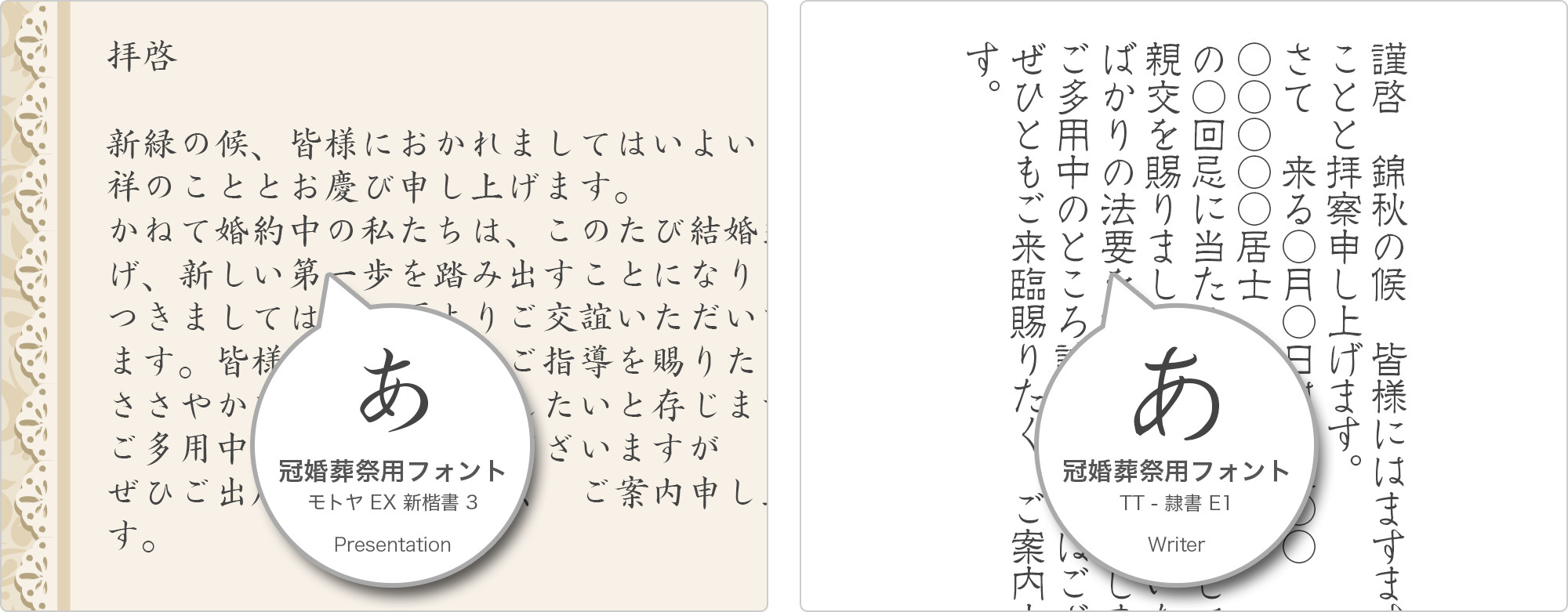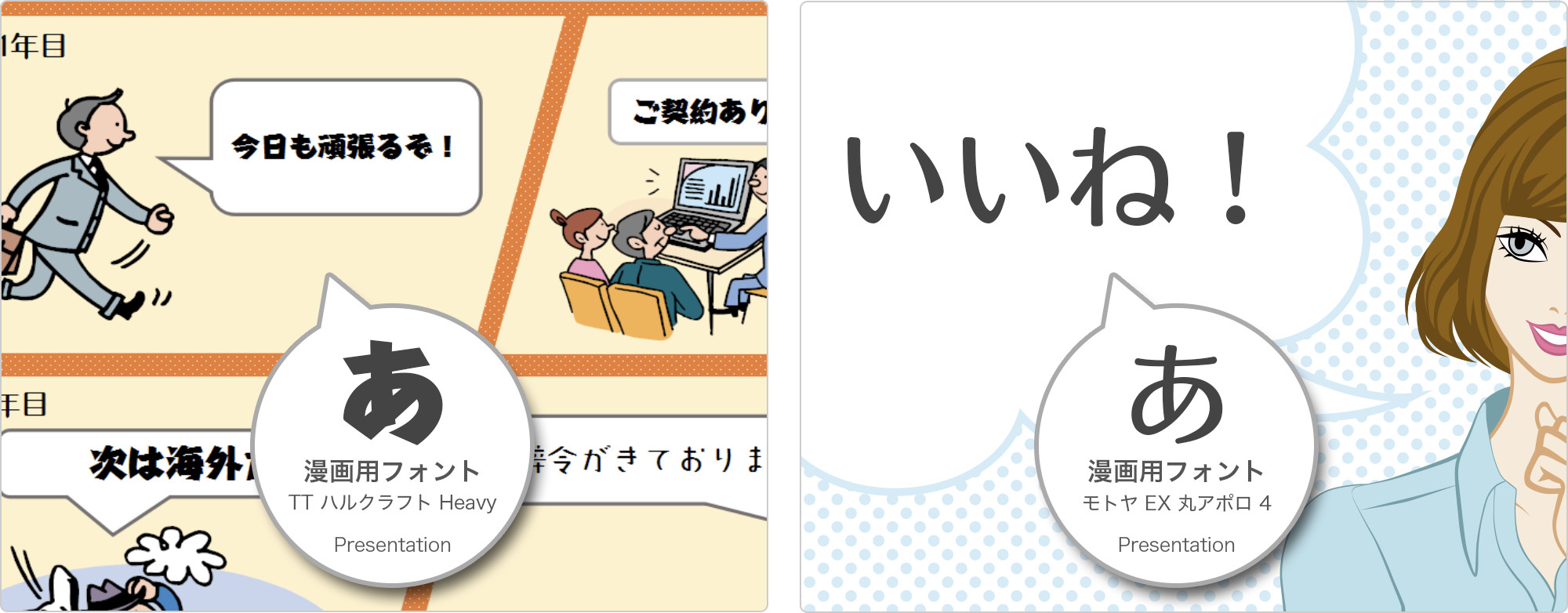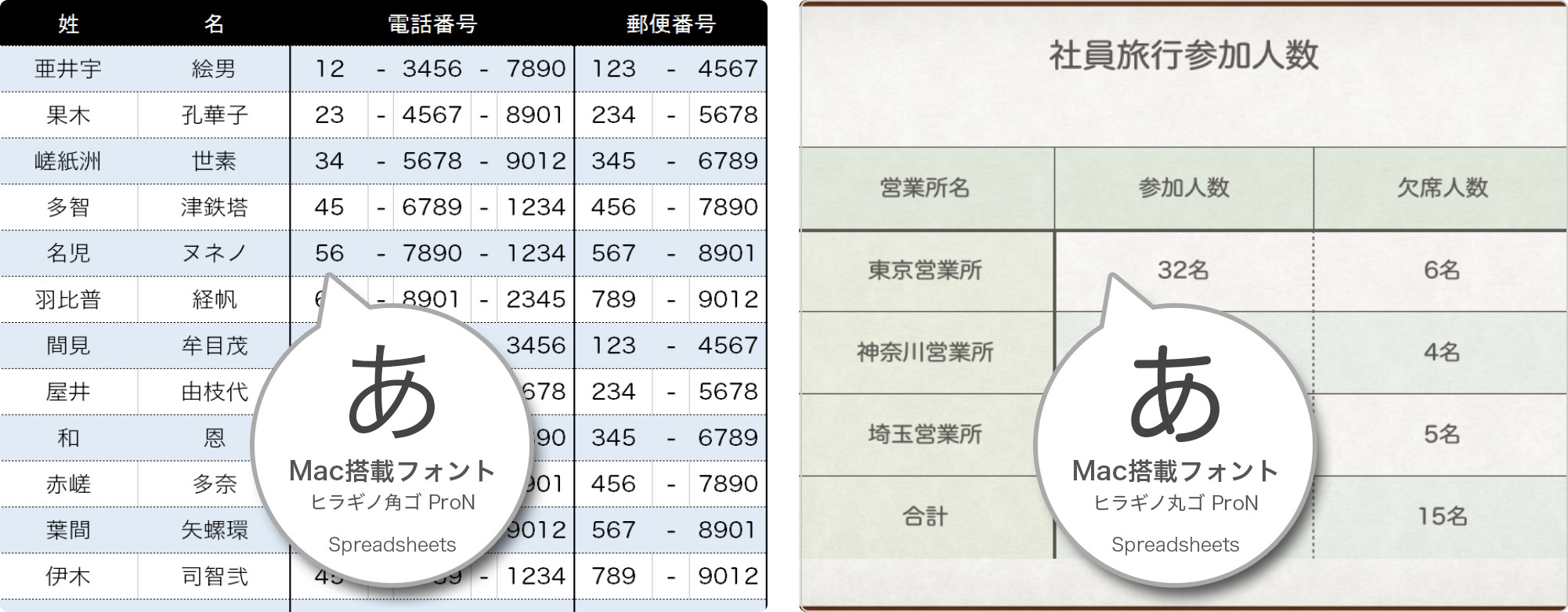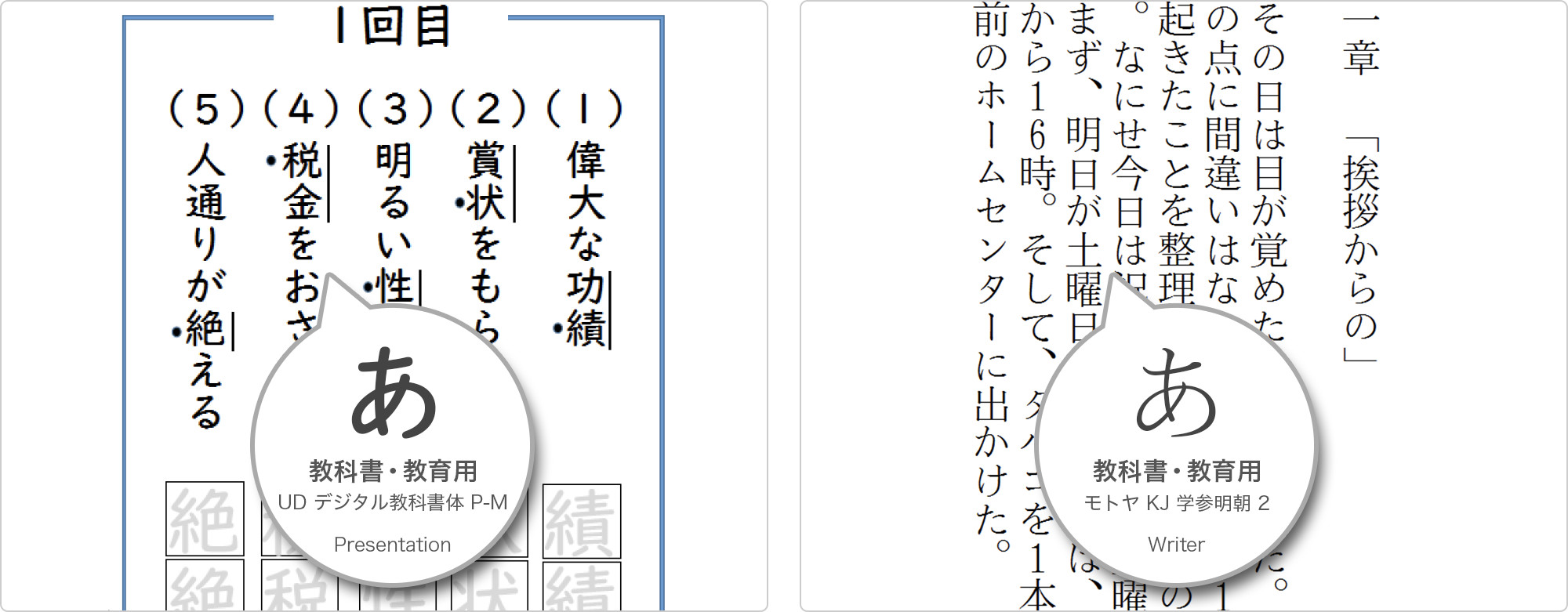
チラシや資料作成に役立つ最大35書体を5つのテーマでご用意しています。[/fusion_title][/fusion_builder_column][/fusion_builder_row][/fusion_builder_container][fusion_builder_container type=”flex” hundred_percent=”no” hundred_percent_height=”no” min_height_medium=”” min_height_small=”” min_height=”” hundred_percent_height_scroll=”no” align_content=”stretch” flex_align_items=”stretch” flex_justify_content=”center” flex_column_spacing=”” hundred_percent_height_center_content=”yes” equal_height_columns=”no” container_tag=”div” menu_anchor=”” hide_on_mobile=”no” status=”published” publish_date=”” class=”py-7″ id=”” margin_top_medium=”” margin_bottom_medium=”” margin_top_small=”” margin_bottom_small=”” margin_top=”0″ margin_bottom=”60″ padding_top_medium=”” padding_right_medium=”” padding_bottom_medium=”” padding_left_medium=”” padding_top_small=”” padding_right_small=”” padding_bottom_small=”” padding_left_small=”” padding_top=”0″ padding_right=”” padding_bottom=”0″ padding_left=”” link_color=”” hue=”” saturation=”” lightness=”” alpha=”” link_hover_color=”” border_sizes_top=”0px” border_sizes_right=”0px” border_sizes_bottom=”0px” border_sizes_left=”0px” border_color=”” border_style=”solid” box_shadow=”no” box_shadow_vertical=”” box_shadow_horizontal=”” box_shadow_blur=”0″ box_shadow_spread=”0″ box_shadow_color=”” box_shadow_style=”” z_index=”” overflow=”” gradient_start_color=”” gradient_end_color=”” gradient_start_position=”0″ gradient_end_position=”100″ gradient_type=”linear” radial_direction=”center center” linear_angle=”180″ background_color=”” background_image=”” skip_lazy_load=”” background_position=”left top” background_repeat=”no-repeat” fade=”no” background_parallax=”none” enable_mobile=”no” parallax_speed=”0.3″ background_blend_mode=”none” video_mp4=”” video_webm=”” video_ogv=”” video_url=”” video_aspect_ratio=”16:9″ video_loop=”yes” video_mute=”yes” video_preview_image=”” render_logics=”” absolute=”off” absolute_devices=”small,medium,large” sticky=”off” sticky_devices=”small-visibility,medium-visibility,large-visibility” sticky_background_color=”” sticky_height=”” sticky_offset=”” sticky_transition_offset=”0″ scroll_offset=”0″ animation_type=”” animation_direction=”left” animation_speed=”0.3″ animation_offset=”” filter_hue=”0″ filter_saturation=”100″ filter_brightness=”100″ filter_contrast=”100″ filter_invert=”0″ filter_sepia=”0″ filter_opacity=”100″ filter_blur=”0″ filter_hue_hover=”0″ filter_saturation_hover=”100″ filter_brightness_hover=”100″ filter_contrast_hover=”100″ filter_invert_hover=”0″ filter_sepia_hover=”0″ filter_opacity_hover=”100″ filter_blur_hover=”0″][fusion_builder_row][fusion_builder_column type=”1_5″ layout=”1_5″ last=”false” spacing=”yes” center_content=”no” hide_on_mobile=”no” background_color=”” background_image=”” background_repeat=”no-repeat” background_position=”left top” hover_type=”none” link=”” border_position=”all” border_color=”” border_style=”” padding_top=”” padding_right=”” padding_bottom=”” padding_left=”” margin_top=”” margin_bottom=”” animation_type=”” animation_direction=”” animation_speed=”0.1″ animation_offset=”” class=”” id=”” min_height=”” border_sizes_top=”0px” border_sizes_bottom=”0px” border_sizes_left=”0px” border_sizes_right=”0px” first=”true” spacing_right=”2%”][fusion_imageframe image_id=”19579″ max_width=”200″ style_type=”none” stylecolor=”” hover_type=”none” bordersize=”0px” bordercolor=”” borderradius=”0″ align=”center” lightbox=”no” gallery_id=”” lightbox_image=”” alt=”” link=”#001″ linktarget=”_self” hide_on_mobile=”no” class=”” id=”” animation_type=”” animation_direction=”down” animation_speed=”0.1″ animation_offset=””]https://www.kingsoft.jp/office/wp-content/uploads/0627font-link1.jpg[/fusion_imageframe][/fusion_builder_column][fusion_builder_column type=”1_5″ layout=”1_5″ last=”false” spacing=”yes” center_content=”no” hide_on_mobile=”no” background_color=”” background_image=”” background_repeat=”no-repeat” background_position=”left top” hover_type=”none” link=”” border_position=”all” border_color=”” border_style=”” padding_top=”” padding_right=”” padding_bottom=”” padding_left=”” margin_top=”” margin_bottom=”” animation_type=”” animation_direction=”” animation_speed=”0.1″ animation_offset=”” class=”” id=”” min_height=”” border_sizes_top=”0px” border_sizes_bottom=”0px” border_sizes_left=”0px” border_sizes_right=”0px” first=”false” spacing_right=”2%” spacing_left=”2%”][fusion_imageframe image_id=”19580″ max_width=”200″ style_type=”none” stylecolor=”” hover_type=”none” bordersize=”0px” bordercolor=”” borderradius=”0″ align=”center” lightbox=”no” gallery_id=”” lightbox_image=”” alt=”” link=”#002″ linktarget=”_self” hide_on_mobile=”no” class=”” id=”” animation_type=”” animation_direction=”down” animation_speed=”0.1″ animation_offset=””]https://www.kingsoft.jp/office/wp-content/uploads/0627font-link2.jpg[/fusion_imageframe][/fusion_builder_column][fusion_builder_column type=”1_5″ layout=”1_5″ last=”false” spacing=”yes” center_content=”no” hide_on_mobile=”no” background_color=”” background_image=”” background_repeat=”no-repeat” background_position=”left top” hover_type=”none” link=”” border_position=”all” border_color=”” border_style=”” padding_top=”” padding_right=”” padding_bottom=”” padding_left=”” margin_top=”” margin_bottom=”” animation_type=”” animation_direction=”” animation_speed=”0.1″ animation_offset=”” class=”” id=”” min_height=”” border_sizes_top=”0px” border_sizes_bottom=”0px” border_sizes_left=”0px” border_sizes_right=”0px” first=”false” spacing_right=”2%” spacing_left=”2%”][fusion_imageframe image_id=”19581″ max_width=”200″ style_type=”none” stylecolor=”” hover_type=”none” bordersize=”0px” bordercolor=”” borderradius=”0″ align=”center” lightbox=”no” gallery_id=”” lightbox_image=”” alt=”” link=”#003″ linktarget=”_self” hide_on_mobile=”no” class=”” id=”” animation_type=”” animation_direction=”down” animation_speed=”0.1″ animation_offset=””]https://www.kingsoft.jp/office/wp-content/uploads/0627font-link3.jpg[/fusion_imageframe][/fusion_builder_column][fusion_builder_column type=”1_5″ layout=”1_5″ last=”false” spacing=”yes” center_content=”no” hide_on_mobile=”no” background_color=”” background_image=”” background_repeat=”no-repeat” background_position=”left top” hover_type=”none” link=”” border_position=”all” border_color=”” border_style=”” padding_top=”” padding_right=”” padding_bottom=”” padding_left=”” margin_top=”” margin_bottom=”” animation_type=”” animation_direction=”” animation_speed=”0.1″ animation_offset=”” class=”” id=”” min_height=”” border_sizes_top=”0px” border_sizes_bottom=”0px” border_sizes_left=”0px” border_sizes_right=”0px” first=”false” spacing_right=”2%” spacing_left=”2%”][fusion_imageframe image_id=”19582″ max_width=”200″ style_type=”none” stylecolor=”” hover_type=”none” bordersize=”0px” bordercolor=”” borderradius=”0″ align=”center” lightbox=”no” gallery_id=”” lightbox_image=”” alt=”” link=”#004″ linktarget=”_self” hide_on_mobile=”no” class=”” id=”” animation_type=”” animation_direction=”down” animation_speed=”0.1″ animation_offset=””]https://www.kingsoft.jp/office/wp-content/uploads/0627font-link4.jpg[/fusion_imageframe][/fusion_builder_column][fusion_builder_column type=”1_5″ layout=”1_5″ last=”true” spacing=”yes” center_content=”no” hide_on_mobile=”no” background_color=”” background_image=”” background_repeat=”no-repeat” background_position=”left top” hover_type=”none” link=”” border_position=”all” border_color=”” border_style=”” padding_top=”” padding_right=”” padding_bottom=”” padding_left=”” margin_top=”” margin_bottom=”” animation_type=”” animation_direction=”” animation_speed=”0.1″ animation_offset=”” class=”” id=”” min_height=”” border_sizes_top=”0px” border_sizes_bottom=”0px” border_sizes_left=”0px” border_sizes_right=”0px” first=”false” spacing_left=”2%”][fusion_imageframe image_id=”19583″ max_width=”200″ style_type=”none” stylecolor=”” hover_type=”none” bordersize=”0px” bordercolor=”” borderradius=”0″ align=”center” lightbox=”no” gallery_id=”” lightbox_image=”” alt=”” link=”#005″ linktarget=”_self” hide_on_mobile=”no” class=”” id=”” animation_type=”” animation_direction=”down” animation_speed=”0.1″ animation_offset=””]https://www.kingsoft.jp/office/wp-content/uploads/0627font-link5.jpg[/fusion_imageframe][/fusion_builder_column][fusion_builder_column type=”1_2″ layout=”1_2″ align_self=”stretch” content_layout=”column” align_content=”center” valign_content=”flex-start” content_wrap=”wrap” spacing=”” center_content=”no” link=”” target=”_self” link_description=”” min_height=”” hide_on_mobile=”small-visibility,medium-visibility,large-visibility” sticky_display=”normal,sticky” class=”mt-6″ id=”” background_image_id=”” type_medium=”” type_small=”” order_medium=”0″ order_small=”0″ spacing_left_medium=”” spacing_right_medium=”” spacing_left_small=”” spacing_right_small=”” spacing_left=”” spacing_right=”” margin_top_medium=”” margin_bottom_medium=”” margin_top_small=”” margin_bottom_small=”” margin_top=”” margin_bottom=”” padding_top_medium=”” padding_right_medium=”” padding_bottom_medium=”” padding_left_medium=”” padding_top_small=”” padding_right_small=”” padding_bottom_small=”” padding_left_small=”” padding_top=”” padding_right=”” padding_bottom=”” padding_left=”” hover_type=”none” border_sizes_top=”0″ border_sizes_right=”0″ border_sizes_bottom=”0″ border_sizes_left=”0″ border_color=”” hue=”” saturation=”” lightness=”” alpha=”” border_style=”solid” border_radius_top_left=”” border_radius_top_right=”” border_radius_bottom_left=”” box_shadow=”no” box_shadow_vertical=”” box_shadow_horizontal=”” box_shadow_blur=”0″ box_shadow_spread=”0″ box_shadow_color=”” box_shadow_style=”” overflow=”” background_type=”single” gradient_start_color=”” gradient_end_color=”” gradient_start_position=”0″ gradient_end_position=”100″ gradient_type=”linear” radial_direction=”center center” linear_angle=”180″ background_color=”” background_image=”” background_position=”left top” background_repeat=”no-repeat” background_blend_mode=”none” render_logics=”” filter_type=”regular” filter_hue=”0″ filter_saturation=”100″ filter_brightness=”100″ filter_contrast=”100″ filter_invert=”0″ filter_sepia=”0″ filter_opacity=”100″ filter_blur=”0″ filter_hue_hover=”0″ filter_saturation_hover=”100″ filter_brightness_hover=”100″ filter_contrast_hover=”100″ filter_invert_hover=”0″ filter_sepia_hover=”0″ filter_opacity_hover=”100″ filter_blur_hover=”0″ animation_type=”” animation_direction=”left” animation_speed=”0.3″ animation_offset=”” last=”true” border_position=”all” first=”true”][fusion_code]PGEgaHJlZj0iaHR0cHM6Ly9wYXkua2luZ3NvZnQuanAvc2hvcHBpbmcvcHJvZHVjdHMvbGlzdC5waHA/Y2F0ZWdvcnlfaWQ9NDQiIGNsYXNzPSJ3cHNfZGxfYnQiIHRhcmdldD0iX2JsYW5rIiByZWw9Im5vb3BlbmVyIj7jgZTos7zlhaXjga/jgZPjgaHjgok8L2E+[/fusion_code][/fusion_builder_column][/fusion_builder_row][/fusion_builder_container][fusion_builder_container admin_label=”POP” type=”flex” hundred_percent=”no” hundred_percent_height=”no” min_height_medium=”” min_height_small=”” min_height=”” hundred_percent_height_scroll=”no” align_content=”stretch” flex_align_items=”stretch” flex_justify_content=”center” flex_column_spacing=”” hundred_percent_height_center_content=”yes” equal_height_columns=”no” container_tag=”div” menu_anchor=”” hide_on_mobile=”small-visibility,medium-visibility,large-visibility” status=”published” publish_date=”” class=”py-7″ id=”001″ margin_top_medium=”” margin_bottom_medium=”” margin_top_small=”” margin_bottom_small=”” margin_top=”0″ margin_bottom=”100″ padding_top_medium=”” padding_right_medium=”” padding_bottom_medium=”” padding_left_medium=”” padding_top_small=”” padding_right_small=”” padding_bottom_small=”” padding_left_small=”” padding_top=”0″ padding_right=”” padding_bottom=”0″ padding_left=”” link_color=”” hue=”” saturation=”” lightness=”” alpha=”” link_hover_color=”” border_sizes_top=”” border_sizes_right=”” border_sizes_bottom=”” border_sizes_left=”” border_color=”” border_style=”solid” box_shadow=”no” box_shadow_vertical=”” box_shadow_horizontal=”” box_shadow_blur=”0″ box_shadow_spread=”0″ box_shadow_color=”” box_shadow_style=”” z_index=”” overflow=”” gradient_start_color=”” gradient_end_color=”” gradient_start_position=”0″ gradient_end_position=”100″ gradient_type=”linear” radial_direction=”center center” linear_angle=”180″ background_color=”” background_image=”” skip_lazy_load=”” background_position=”center center” background_repeat=”no-repeat” fade=”no” background_parallax=”none” enable_mobile=”no” parallax_speed=”0.3″ background_blend_mode=”none” video_mp4=”” video_webm=”” video_ogv=”” video_url=”” video_aspect_ratio=”16:9″ video_loop=”yes” video_mute=”yes” video_preview_image=”” render_logics=”” absolute=”off” absolute_devices=”small,medium,large” sticky=”off” sticky_devices=”small-visibility,medium-visibility,large-visibility” sticky_background_color=”” sticky_height=”” sticky_offset=”” sticky_transition_offset=”0″ scroll_offset=”0″ animation_type=”” animation_direction=”left” animation_speed=”0.3″ animation_offset=”” filter_hue=”0″ filter_saturation=”100″ filter_brightness=”100″ filter_contrast=”100″ filter_invert=”0″ filter_sepia=”0″ filter_opacity=”100″ filter_blur=”0″ filter_hue_hover=”0″ filter_saturation_hover=”100″ filter_brightness_hover=”100″ filter_contrast_hover=”100″ filter_invert_hover=”0″ filter_sepia_hover=”0″ filter_opacity_hover=”100″ filter_blur_hover=”0″][fusion_builder_row][fusion_builder_column type=”1_1″ layout=”1_1″ spacing=”yes” center_content=”no” link=”” target=”_self” min_height=”” hide_on_mobile=”no” class=”” id=”” background_color=”” background_image=”” background_position=”left top” undefined=”” background_repeat=”no-repeat” hover_type=”none” border_color=”#eeeeee” border_style=”solid” border_position=”all” padding_top=”” padding_right=”” padding_bottom=”” padding_left=”” margin_top=”” margin_bottom=”60px” animation_type=”” animation_direction=”down” animation_speed=”0.1″ animation_offset=”” last=”true” border_sizes_top=”0″ border_sizes_bottom=”0″ border_sizes_left=”0″ border_sizes_right=”0″ first=”true”][fusion_title margin_top=”” margin_bottom=”60″ hide_on_mobile=”small-visibility,medium-visibility,large-visibility” class=”” id=”” size=”2″ content_align=”center” style_type=”double solid” sep_color=””]
POP作成
チラシ・広告などインパクトのある表現に適したフォントたち
教科書・教育
学習指導要領に基づく教科書体および準拠する書体を含む教育シーンに適したフォントたち